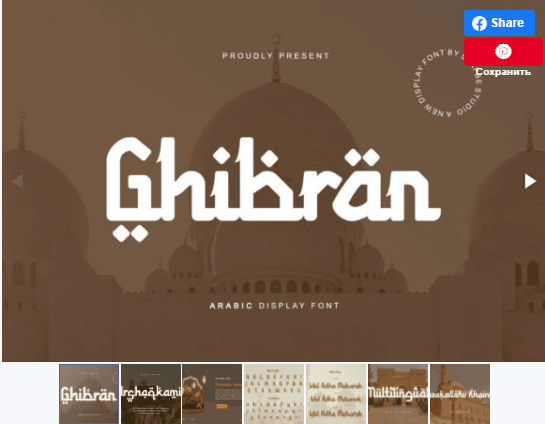
Ghibran Font
Ghibran - это крутой и уникально выглядящий дисплейный шрифт, вдохновленный арабским искусством. Его стильные альтернативы и лигатуры делают этот шрифт идеальным для любого проекта. Ghibran имеет кодировку PUA, что означает, что вы можете легко получить доступ ко всем глифам и росчеркам!